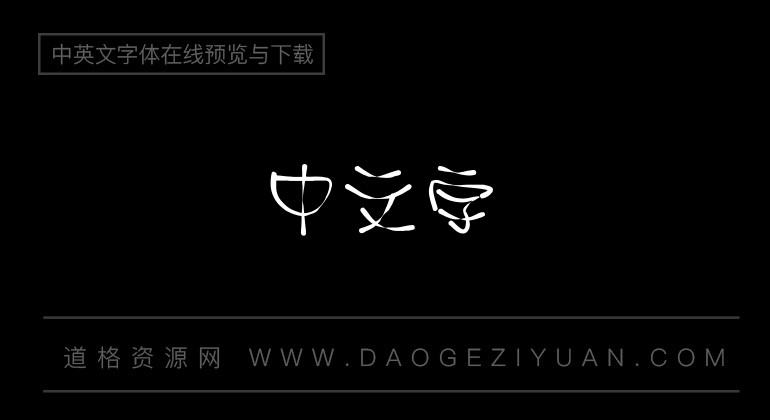
金梅浪漫古印字体
金梅浪漫古印字体是一款源自古老文化的字体,它拥有浓郁的古典气息,蕴含着深厚的历史文化底蕴。金梅浪漫古印字体以金梅纹为主要元素,结合古老的印章文字,给人一种浪漫的感觉。金梅浪漫古印字体笔画流畅,结构精细,每一个字都充满着古典的韵味,可以用来装饰各种文字、文档、图片等,让文字更加美观大方。
金梅浪漫古印字体是一款非常不错的手写艺术字体,具有很好的视觉感,适合于文化类的宣传设计、商业类品牌的广告和产品包装设计以及个性化文字排版等较多场景。